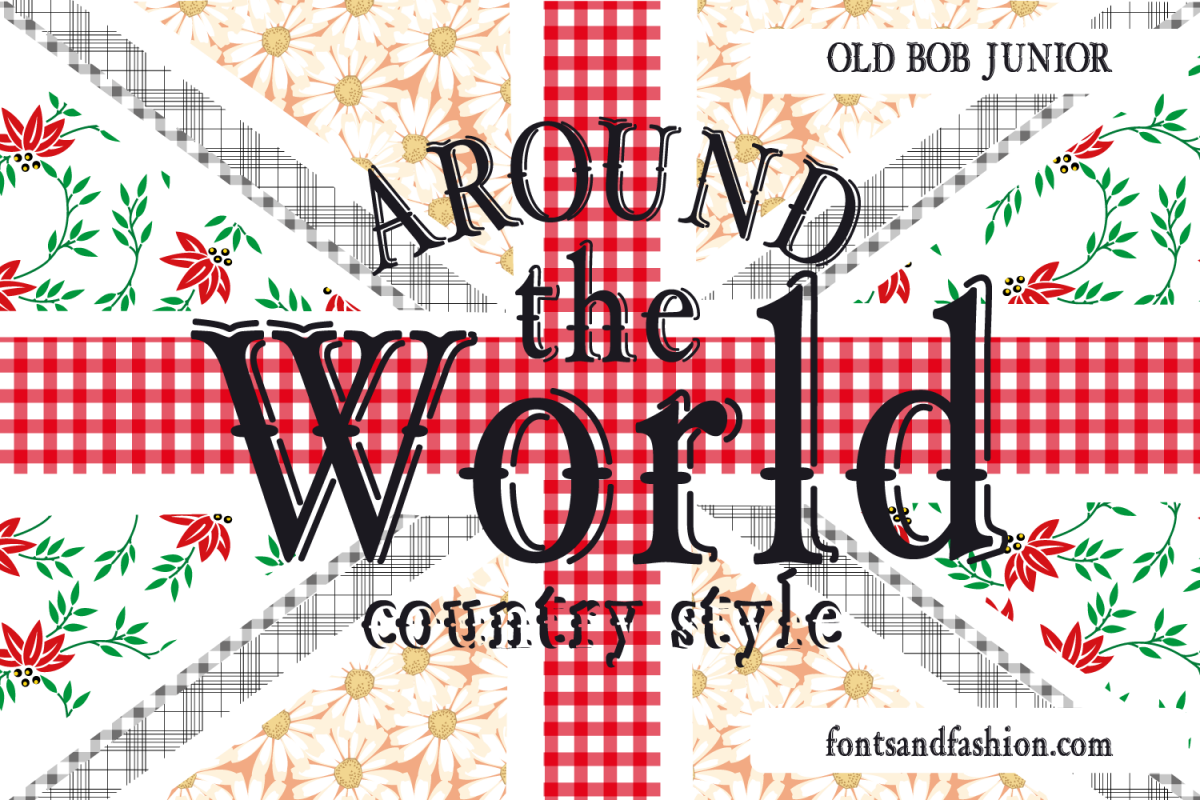
Old Bob junior
OLD BOB junior Old Bob junior è stato creato dalla versione base del font, con l'aggiunta di un contorno alla destra delle lettere, un'ombra che lo arricchisce e gli conferisce un'interessante funzionalità aggiuntiva. Per chiunque desideri creare opere più accattivanti ... La famiglia Old Bob ti sta aspettando ... disponibile nella versione singola o nella versione "pack", aiuterà la tua creatività a